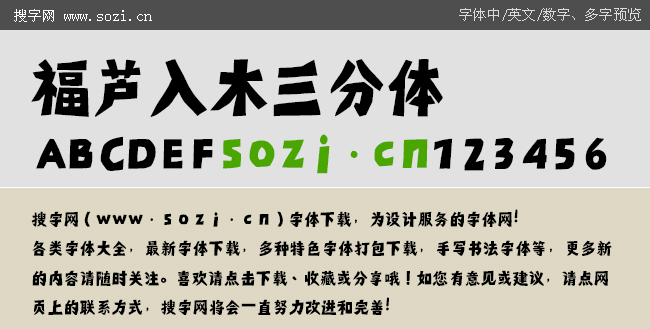
福芦入木三分体
搜字网提供一款福芦入木三分体中文字体下载,福芦入木三分体通过模拟刻刀在木头上雕琢的动态过程,在笔画间塑造自然的顿挫、粗细变化,还原刻刀入木时“刀走纹理”的真实痕迹;强化手工雕刻的独特肌理,保留笔触毛边与刻痕的不规则感,让每一处细节都流露手工创作的温度。摒弃机械美学的规整,重现木刻艺术的技法精髓,传递匠人以刀为笔的创作匠心。适合包装设计、海报设计、广告设计等应用。